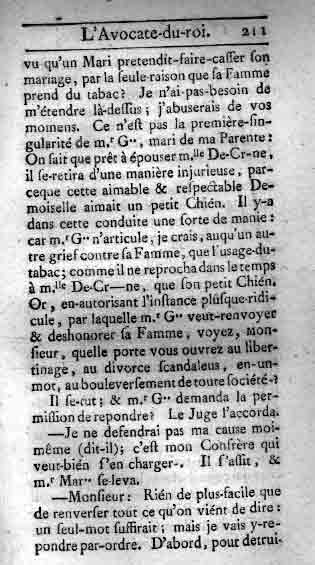
Soyez indulgent pour l'abréviation. Regardez, sur l'image jointe, comment faisait au 18e siècle (pas de petites caps ni de supérieures, désolé) notre grand Restif de la Bretonne dans ses _Contemporaines._ Notez au passage sa grande liberté de composition. D'aucuns diraient son laxisme. Relisez également ce que disait sur le sujet celui qui fut une grande part de l'âme de cette liste et que, hélas, je n'ai pas connu. Allez, c'est décidé, je me range aux côtés de m.r Nicolas, et j'abrège comme lui... :-) Votre bien dévoué, CLS ----- Original Message ----- From: "Denis Verges" <Denis.verges@xxxxxxxxxx> To: <typographie@xxxxxxxxxxxxxxx> Sent: Tuesday, November 30, 2004 3:55 PM Subject: Re: [typo] Massin assassin d'Azerty > Il commence par lui faire un compliment : "Mr Massin (que j'ai vénéré > pour « La Lettre et l'Image »)" en lui donnant du "Monsieur". > > Maintenant, avec un peu de bonne foi, si cet ouvrage n'avait pas été > signé Massin, quel accueil lui auriez-vous réservé ? un éditeur ne peut > cautionner les fautes, les erreurs, les coquilles qu'Éric décrit, lui, > avec beaucoup de professionnalisme, et surtout d'humour... > > Je ne me lasse pas de "on dirait qu'il a dicté son bouquin par GSM à > l'éditeur "... > Bonjour, Je me frotte les yeux : - Mr. Massin au lieu de M. - mn au lieu de min (minute) - des quotes au lieu des guillemets en chevrons Suis-je vraiment sur une liste de typographie ? Denis Vergès